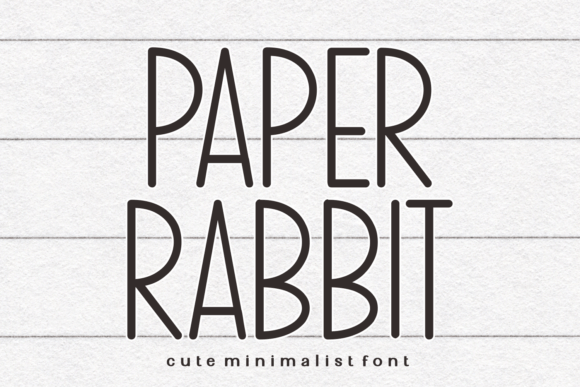
Paper Rabbit
์ •๋ฐ€ํ•˜๊ฒŒ ์ œ์ž‘๋œ Paper Rabbit๋Š” ๊น”๋”ํ•œ ๋ฒกํ„ฐ, ๋ถ€๋“œ๋Ÿฌ์šด ํƒ€์ดํฌ๊ทธ๋ž˜ํ”ผ ๋ฐ ์•ˆ์‹ฌํ•  ์ˆ˜ ์žˆ๋Š” ์ƒ์—…์šฉ ๋ผ์ด์„ ์Šค๋ฅผ ์ œ๊ณตํ•ฉ๋‹ˆ๋‹ค.